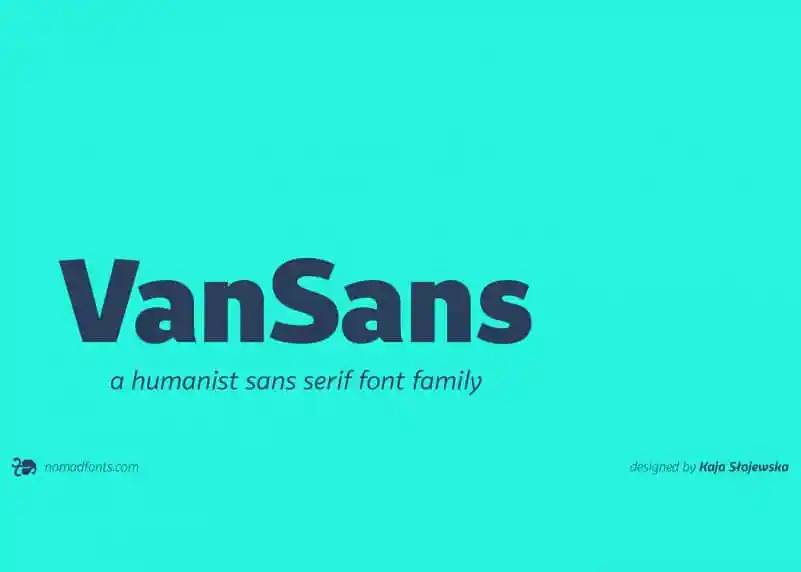
Introduzimos VanSans Sans Serif Font, uma elegante e moderna fórmula de tipo serifada criada pela Nomad Fonts com caracteres atraentes. Inspirada na cidade de Vancouver, essa fonte mescla um sentido industrial com a amabilidade e abertura da população local. Com um alto x-height e contornos abertos, ela é clara e legível tanto em ambientes impressos quanto digitais. VanSans tem uma família que se adaptará a qualquer hierarquia de tipo que um designer possa precisar, oferecendo pesos desde fino até grosso. Ele também suporta ambos os alfabetos extensos latino-cyrillico e oferece múltiplas funcionalidades do OpenType. VanSans funciona perfeitamente para o editorial, identidade visual na web e publicidade – e está pronto para ser desafiado por você.